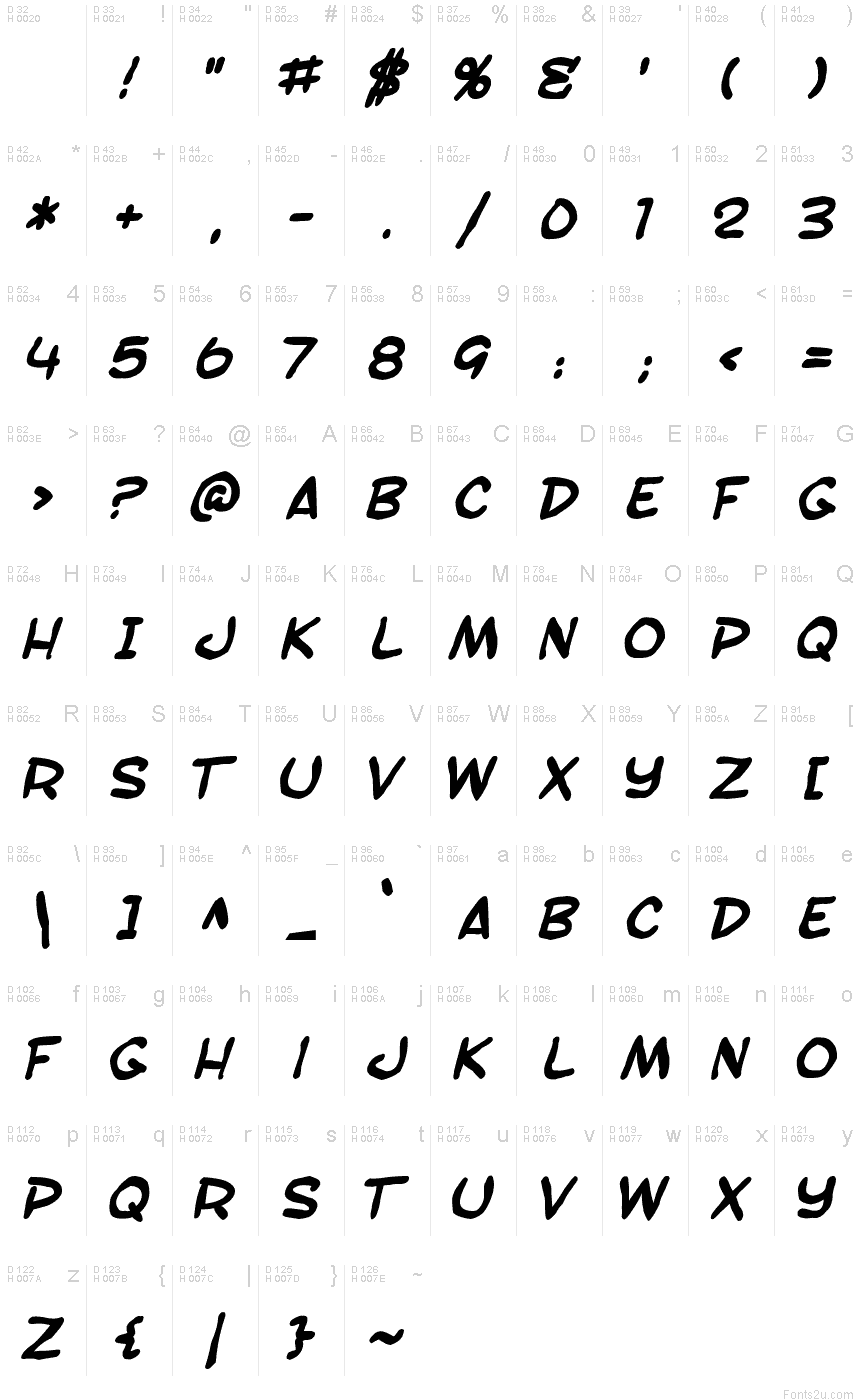
SF Toontime Blotch Bold Italic
SF Toontime Blotch Bold Italic od ShyFoundry to darmowy krój pisma w stylu cartoon, z grubymi literami, które wyglądają, jakby zostały namalowane szybkim, soczystym pociągnięciem pędzla. Litery są dynamiczne i szerokie, mają zaokrąglone rogi, wyraźną grubość oraz swobodne pochylenie, które nadaje alfabetowi komiksowego charakteru.
Idealnie nadaje się do plakatów, ulotek dla dzieci, komiksowych nagłówków, tytułów gier i zabawnych opakowań, gdzie ten darmowy font wnosi ręcznie malowaną energię, nie będąc przy tym zbyt schludnym czy wyrafinowanym. Dzięki temu, że wielkie litery są masywne i proste, sprawdza się również w krótkich tekstach na okładkach i szkicach logotypów, które potrzebują odważnego, lekko nieokiełznanego wyrazu.
ShyFoundry
Derek Vogelpohl